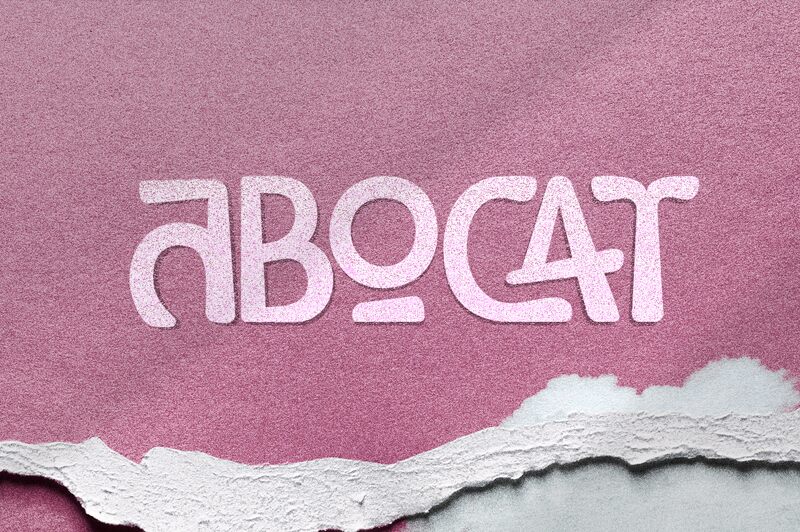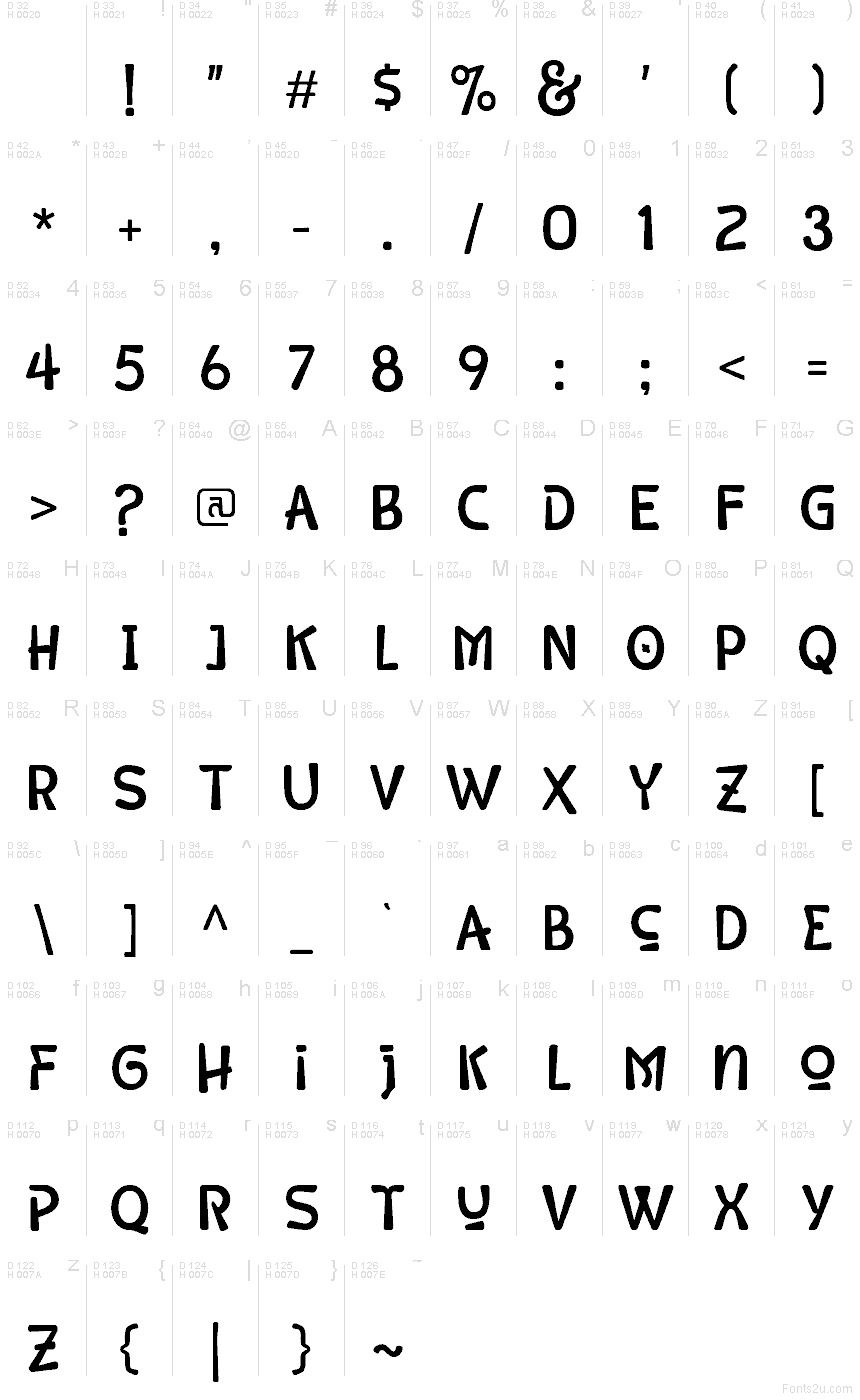
Abocat
Abocat, créée par Grontype, est une police de caractères d'affichage gratuite. Avec ses formes arrondies, irrégulières et ses courbes douces, elle évoque une création artisanale, presque cartoon. La structure reste simple, mais ses courbures, ses extrémités évasées et ses légères imperfections rendent l'alphabet moins rigide et beaucoup plus informel qu'une police de titrage classique.
Abocat est parfaite pour les titres d'affiches, les logos, les menus de cafés, les étiquettes de produits et les visuels destinés aux réseaux sociaux, où une touche amicale et personnalisée aide le message à se démarquer. Cette police gratuite est idéale pour les projets jeunesse ou les événements informels, car ses formes restent lisibles et distinctives sans jamais devenir trop chargées.